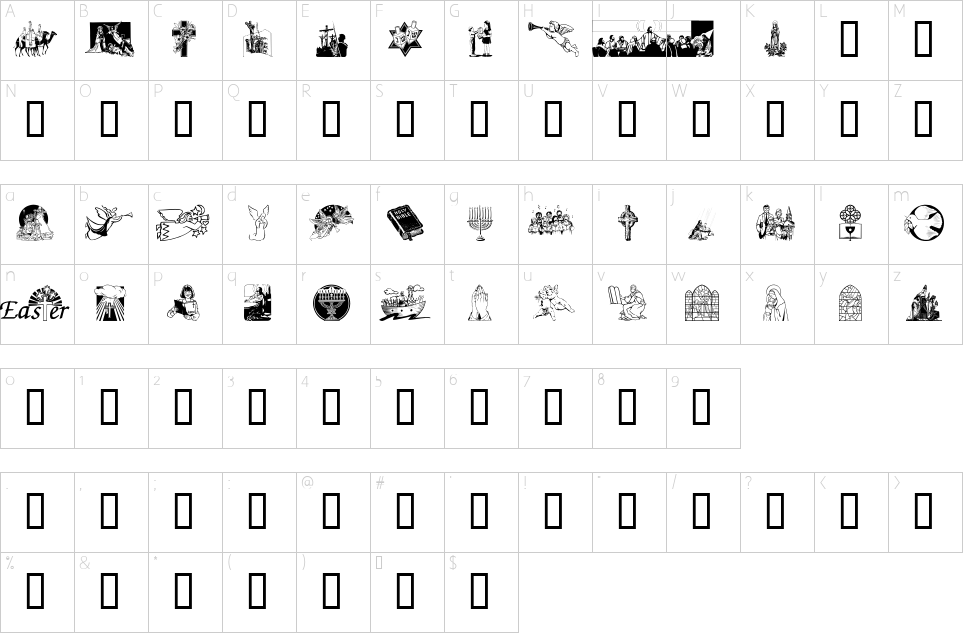
Descubra a beleza de JFC font, uma elegante e versátil opção para seus projetos digitais. Desenvolvida pelo Designer Gem Fonts, JFC font é uma fonte perfeita para quem procura um visual limpo e sofisticado. Com um design cuidadosamente planejado, ela traz uma harmonia perfeita entre simplicidade e expressividade. Este projeto de fonte gratuita está disponível para download tanto no Windows quanto no Mac, e já foi baixada mais de 4.118 vezes por criadores de conteúdo e profissionais de design. Adquira JFC font e enriqueça suas criações com um estilo singular e elegante.